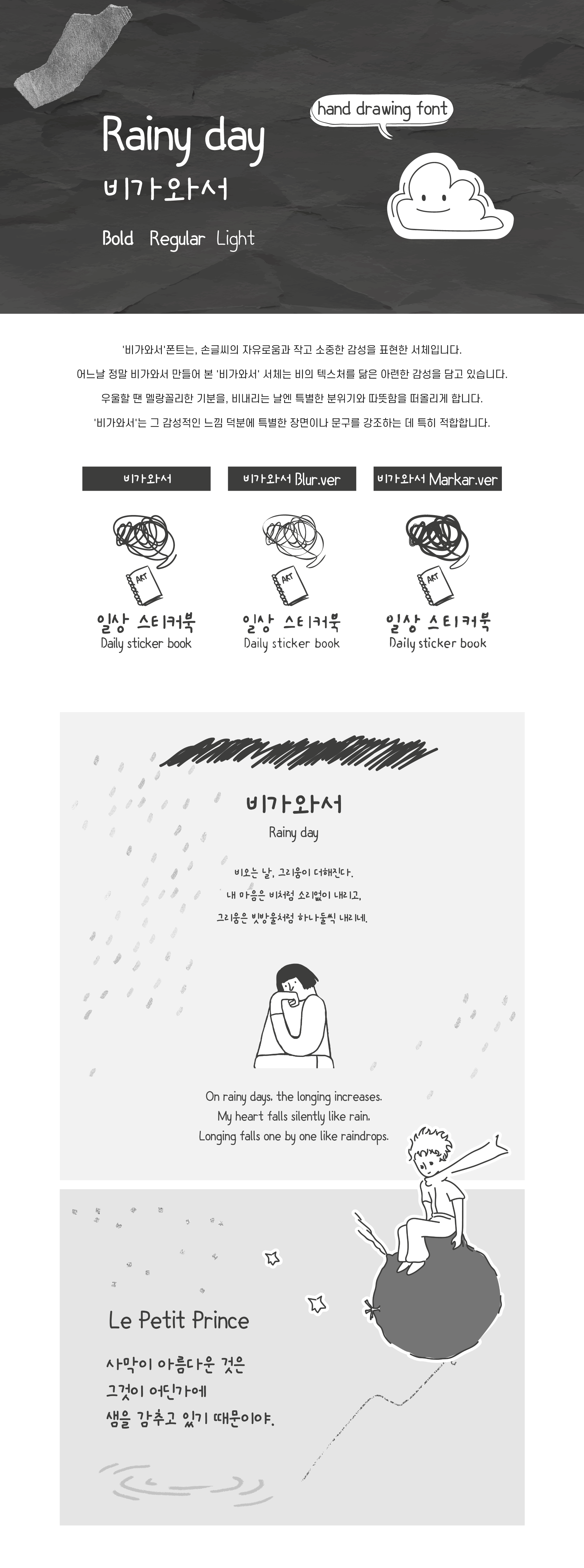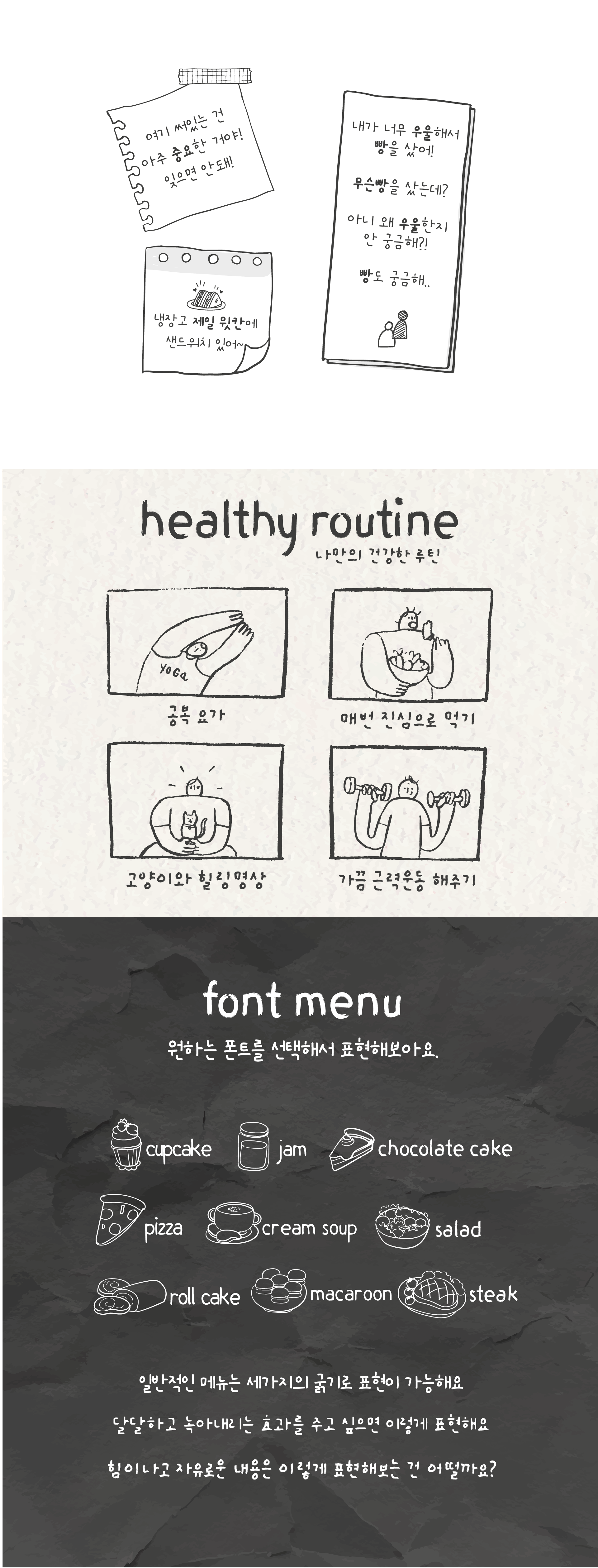
비가와서 5종 세트
'비가와서'폰트는 손글씨의 자유로움과 작고 소중한 감성을 표현한 서체입니다. 어느 날 정말 비가와서 만들어 본 '비가와서'서체는 비의 텍스처를 닮은 아련한 감성을 담고 있습니다. 우울할 땐 멜랑꼴리한 기분을, 비 내리는 날엔 특별한 분위기와 따뜻함을 떠올리게 합니다.